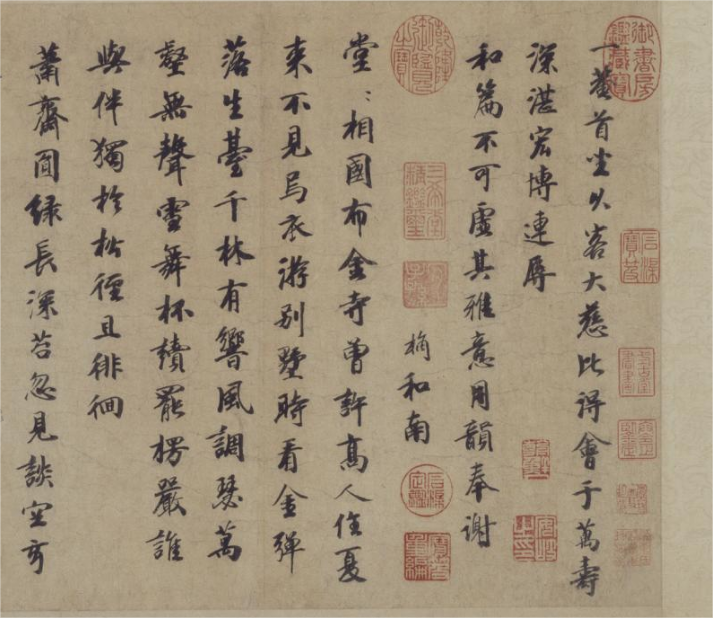
汉标袁桷一菴首座诗帖 By 真迹小字库 商用字体
字体简介: 下载须知:本字库非标准GB2312字库。本字库只包含了袁桷《一菴首座诗帖》真迹上的“313个字”。《一菴首座诗帖》页,元,袁桷书,纸本,行书,纵31.5厘米,横89.7厘米。《一菴首座诗帖》为元三家书法合卷之一,文中“一菴”为元朝僧人释寿宁的号。释寿宁字无为,永嘉人,时任静安寺(在今上海市)住持。此书法整体布置尽其停匀,用笔得于晋唐,颇具法度,行笔柔韧,神采可爱,古意犹存。